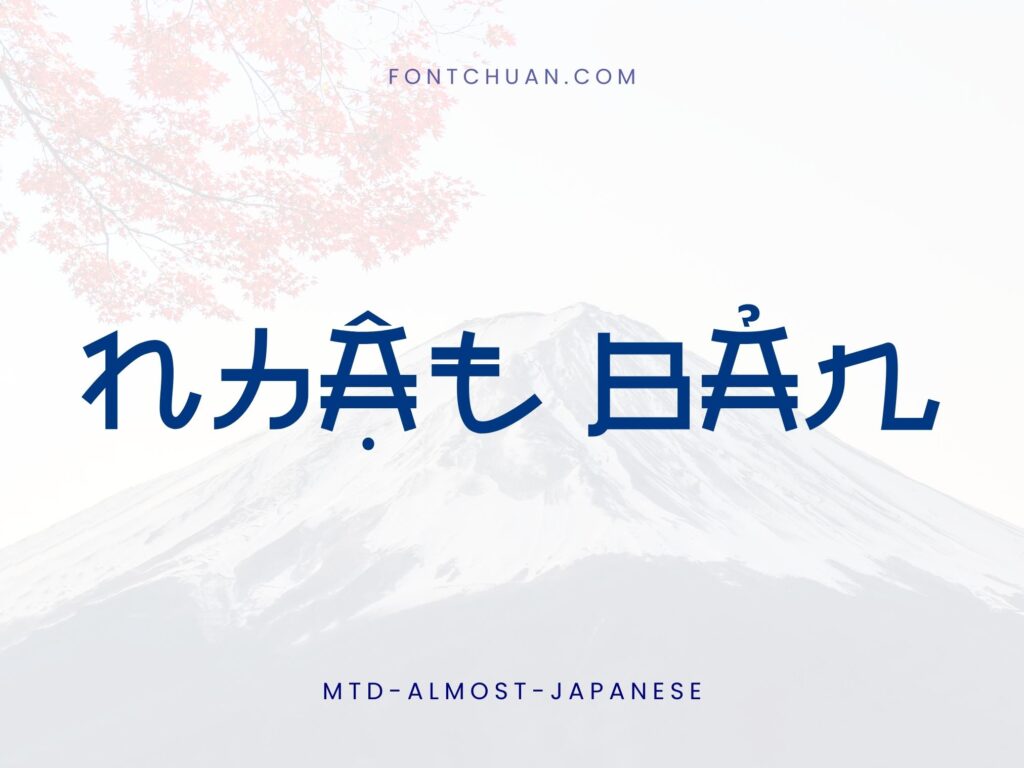
Font Almost Japanese là một kiểu chữ độc đáo được thiết kế bởi Galdino Otten, mang đậm phong cách Á Đông với các nét chữ gợi nhớ đến văn hóa Nhật Bản. Với thiết kế sáng tạo, font này mang lại cảm giác mới lạ và thu hút cho các dự án thiết kế.
Phiên bản Almost Japanese đã được Việt hóa bởi Mộc Hạ, hỗ trợ đầy đủ tiếng Việt cùng hơn 64 ngôn ngữ khác như Anh, Pháp, Tây Ban Nha, Đức, Ý và Bồ Đào Nha, mở rộng khả năng ứng dụng trong thiết kế đa ngôn ngữ. Font này đã được thành viên Font Chuẩn sưu tầm và chia sẻ, đáp ứng nhu cầu của cộng đồng thiết kế. Với thiết kế độc đáo, Almost Japanese phù hợp cho các ứng dụng như thiết kế logo, tiêu đề, bao bì sản phẩm và các ấn phẩm quảng cáo. Các ngành nghề như quảng cáo, giáo dục, công nghệ và ẩm thực có thể tận dụng font này để tạo ra thiết kế ấn tượng và thu hút.